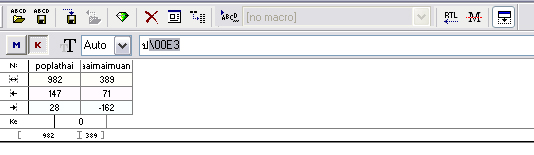
กลับมาอีกครั้งครับ​กับ​สองสามคำ​ถาม​
​จุดกลมๆ​นี่​เลื่อนไปมา​เพื่ออะ​ไรครับ​
​ต้อง​ไว้​บริ​เวณที่​เส้นตัด​กัน​ตลอด​หรือ​ไม่​ ?
​ปุ่ม​ใน​การปรับ​ kerning ​มี​ไว้​ทำ​อะ​ไรบ้างครับ​ ?
​อ่านเจอว่า​ต้อง​กด​ k ​แต่ก็​ไม่​รู้ปุ่ม​อื่นๆ​ ​และ​ผลของมันครับ​
​อีกปัญหาคือพอไปเลื่อนเส้น​ใน​การ​ kerning ​ทำ​ให้​ช่องไฟของตัวอักษร​อื่น​มันเพี้ยน​
​ต้อง​เลื่อนที่ตัวไหนอะครับ​
ข้อนี้ไม่เป็นไรครับ เคลียร์แล้ว ลองทำดูอีกที เริ่มเข้าใจแล้วครับ  :12:
ปัญหาใหม่อีกแล้ว จับทางพวก สระ วรรณยุกต์ พอได้แล้ว
แต่ดันมีปัญหา กับพวกแกงค์หางยาว + สระ หรือวรรณยุกต์ (หลายคนเตือนไว้ก่อนแล้วละ)
เช่น ปีมะโรง ศีลธรรม สีลม ฟิล์ม ฝีดาษ
คือสระมันจะไปดึง ตัวอักษรอื่นๆมาชิดเลย
ต้องแก้ไขอย่างไรครับ ?  :16: :16:
ตัวที่มีช่องไฟความกว้างเป็น 0 อย่างพวกสระ วรรณยุกต์ไทย อย่าจัด kerning นะครับ มันจะดึงตัวถัดมาให้ตามไปด้วย จัดตัวธรรมดาก็พอ  :20:
สมมุติ
น+สระอิ แล้วให้สระอิมันเลื่อนมาข้างหน้า ตัวที่ตามมาจะเลื่อนตาม
ุถ้า สระอิ+สระโอ แล้วให้สระโอเลื่อนออกไป อย่างนี้ได้
แต่ก็ใช่ว่าทุกโปรแกรมจะสามารถให้ kerning ได้นะก๊าบ เพราะฉะนั้นจัดปกติให้ดูดีไว้ก่อนก็น่าจะโอเค
จุดกลมๆที่วงไว้ เค้าเรียก เรฟเฟอร์เรนท์ พอยต์ ครับ
เป็นจุดที่ใช้อ้างอิงในบางคำสั่งครับ
ส่วนใหญ่ จะเป็นชุดคำสั่งใน ทรานฟอร์ม กับ แอคชั่นครับ
แต่ถ้าไม่ได้ใช้ คำสั่งเหล่านั้นจุดที่ว่านั่นก็ไม่มีผลอะไร
ต่อข้อถามที่ว่ามันควรอยู่ตรงจุดที่ตัดกันตลอดไหม
คำตอบคือ มันควรอยู่ตรงนั้นครับ เว้นแต่ว่าเราต้องการใช้
ชุดคำสั่งดังที่กล่าวมาแล้ว และต้องการใช้ เรฟเฟอร์เรนท์
ก็สามารถลากจุดกลมๆที่ว่านั่นไปยังตำแหน่งที่ต้องการได้ครับ
ปล.เมื่อใช้เสร็จแล้วควรเก็บเข้าที่เพื่อความเป็นระเบียบ
แต่ถ้าลืมเก็บก็ไม่เป็นไร เวลาเจนเดี๋ยวโปรแกรมจะจัดระเบียบให้เองครับ :22:
ลองสังเกตที่ ส เสือ ศ ศาลาของตัวอักษรอื่นๆสิครับ ไม่ทำหางเบี่ยงขวา ก็จะทำหางสั้นก่อนถึงสระอิ
สำหรับส เสือ ที่เหมือน ป ปลา ก็ต้องเขียน opentype เพิ่มน่ะครับ (ให้มันมีลักษณะเหมือน ป ปลา)